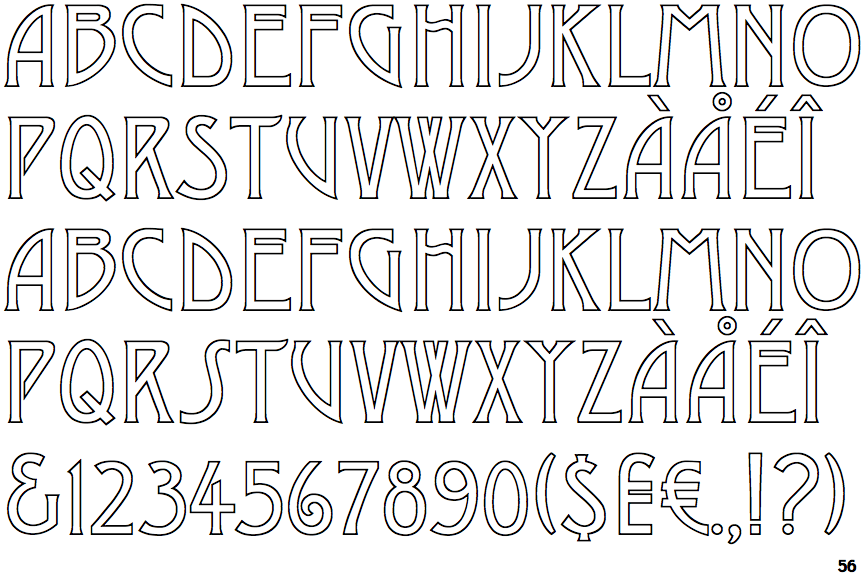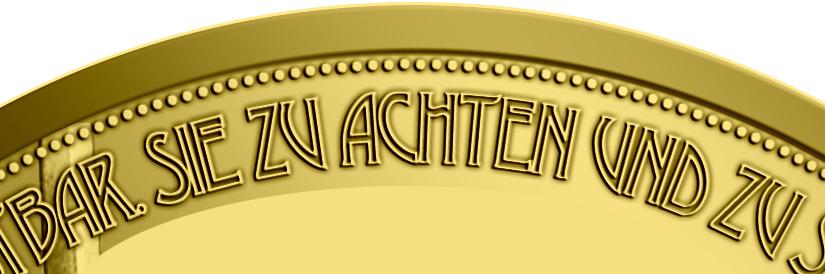
habe hier ein Problem mit einer Typo. Kann mir jemand sagen welche Schrift das ist?
Typeface: Desdemona
Year: 1992 (1900 *)
Copyright: Font Bureau
Publishers: Microsoft Typography and Font Bureau
Alternates: Quaint Gothic SG
Value Pack (Macintosh). No lower-case characters.
*) Origin:
Typeface: Quaint Gothic SG
Designer: Jim Spiece
Year: 1900, 2002
Copyright: Spiece Graphics
Publisher: Spiece Graphics
Additional alternate characters provided. Based on the Quaint Series from the
Dickinson Type Foundry in Boston USA circa 1900. Also known as Desdemona by the
K.K. Hof & K. Brendler Foundry.
Desdemona (Outline), Microsoft Typografie, John McConnell Face Photosetting, 1960s http://www.microsoft.com/typography/fonts/family.aspx?FID=92
Korrektur bzgl der Namensangabe:.............................
Bis 1867: Brendler Carl, Schriftgießer und Graveur; Firma: Carl Brendler & Söhne.
und (?) k. k. Hof-Schriftgießerei und Hof-Gravieranstalt Carl Brendler & Söhne,
Wien Ab 1867 wird die Schriftgießerei so geführt: Karl Brendler und Söhne, K.u.K.
Hof-Schriftgiesserei und Hof-Gravieranstalt (Wien)
Quelle des Fehlers: LUC DEVROYE -> John F. Cumming
Liste der k.u.k. Hoflieferanten 1899 Brendler Carl, Schriftgießer und Graveur;
Firma: Carl Brendler & Söhne.
Kaiserreich Österreich steht für: das Kaisertum der Rudolfskrone 1804 - 1918,
siehe Kaiser von Österreich Kaisertum Österreich, die k. k. Monarchie 1804 - 1867
Österreich-Ungarn, die k. u. k. Doppelmonarchie 1867 - 1918
Die Staatsbibliothek Berlin führt ihn unter ,,Karl Brendler und Söhne, K.u.K.
Hof-Schriftgiesserei und Hof-Gravieranstalt (Wien)''